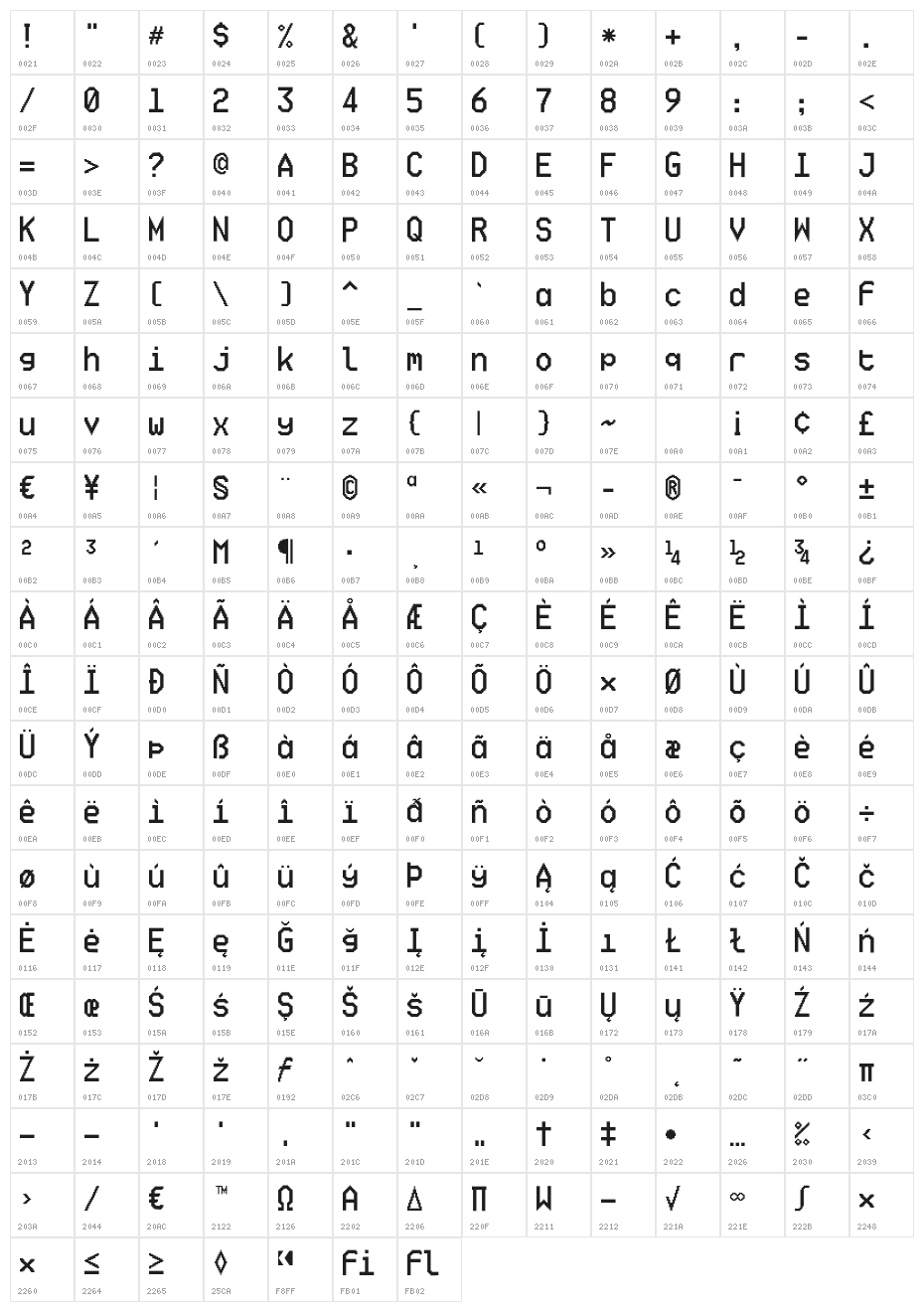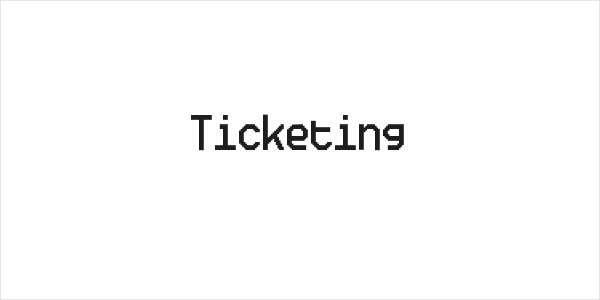
Ticketing Font
| Gesamtstil | Vintage |
| Anwendungsfall | Logos, Headlines, Digital displays |
| Vorgeschlagene Projekte | Ideal for retro video game designs, tech-themed posters, digital art, and any project that requires a vintage digital look. |